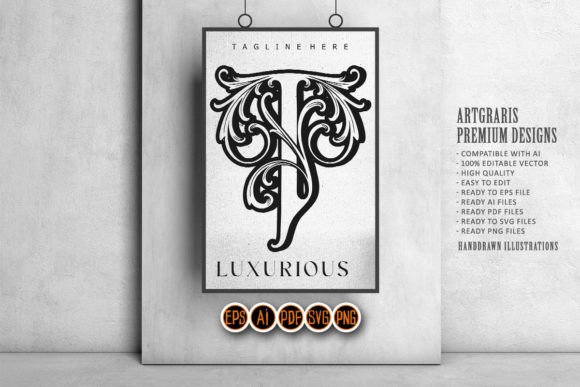
Sophistication Luxury T Lettering
قد يكون العثور على عناصر التصميم المناسبة أمرًا صعبًا، ولكن Sophistication Luxury T Lettering يقدم مجموعة استثنائية ترتقي بعملك على الفور.
سواء كنت تقوم بإنشاء منتجات الطباعة عند الطلب أو دعوات الزفاف أو رسومات وسائل التواصل الاجتماعي، فإن Sophistication Luxury T Lettering هو الخيار المثالي.